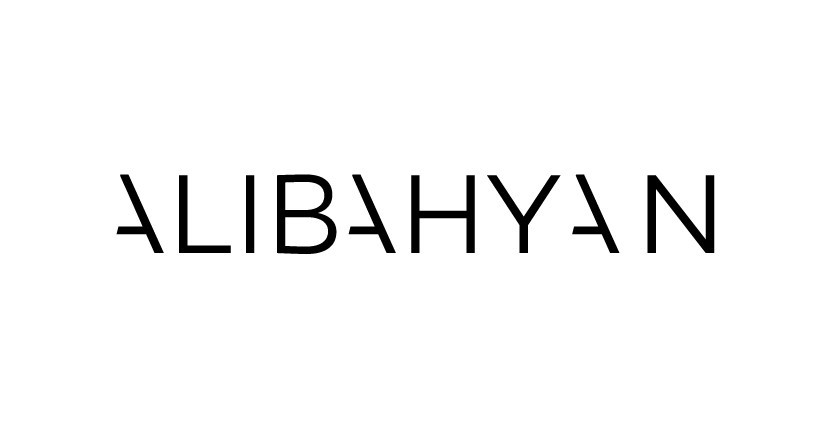
Buna Benzer Font Bilen?
Arkadaşlar bu olması şart değil buna benzer bir font bilen var mı?
Fonttan ziyade a harfinin yarı kısmı silinerek oluşturulmuş bir çalışma gibi geldi bana
Blair ITC veya Raleway
banada öyle gelmişti ilk başta ama sonra çok stabil durmadı durum.. belkide gerçekten öyledir bilemiyorum
A kesilmiş lato ya da nexa benziyor
CANARO (A harfleri düzenlenmiş tabi)